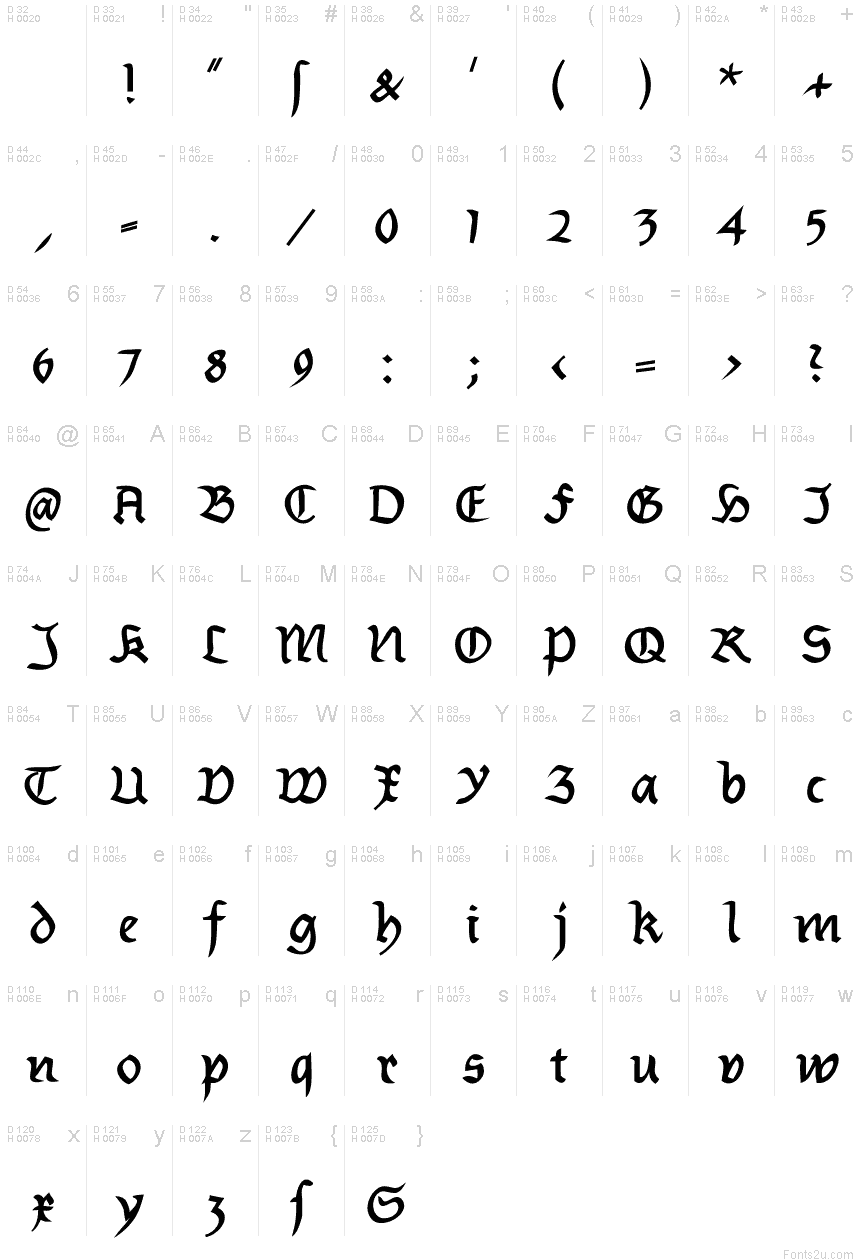
Krój Burtinomatic Demi Bold od MK to darmowy font gotycki o płynnym, atramentowym charakterze, który łagodzi tradycyjną surowość stylu blackletter. Rodzina Burtinomatic zastępuje ostre kolce zaokrąglonymi pociągnięciami i delikatnie rozszerzonymi formami, dzięki czemu przypomina bardziej baśniową księgę niż wykutą w kamieniu inskrypcję. Grube, równe grubości liter sprawiają, że każde słowo jest solidne i czytelne, a dramatyczne krzywizny nadają typografii mrocznego, teatralnego ciepła.
Używając Burtinomatic Demi Bold, nadasz okładkom książek fantasy, tytułom RPG, logotypom gier, plakatom zespołów, ulotkom wydarzeń gotyckich oraz brandingowi tatuaży odważny, magiczny akcent. Ten darmowy font świetnie prezentuje się w większych rozmiarach, gdzie jego wyrzeźbione krzywizny i mroczny rytm mogą naprawdę wybrzmieć. Jako tekst uzupełniający, połącz go z czystym, geometrycznym fontem bezszeryfowym i zachowaj mniejszy, bardziej stonowany styl drugoplanowy, aby Burtinomatic pozostała gwiazdą projektu.